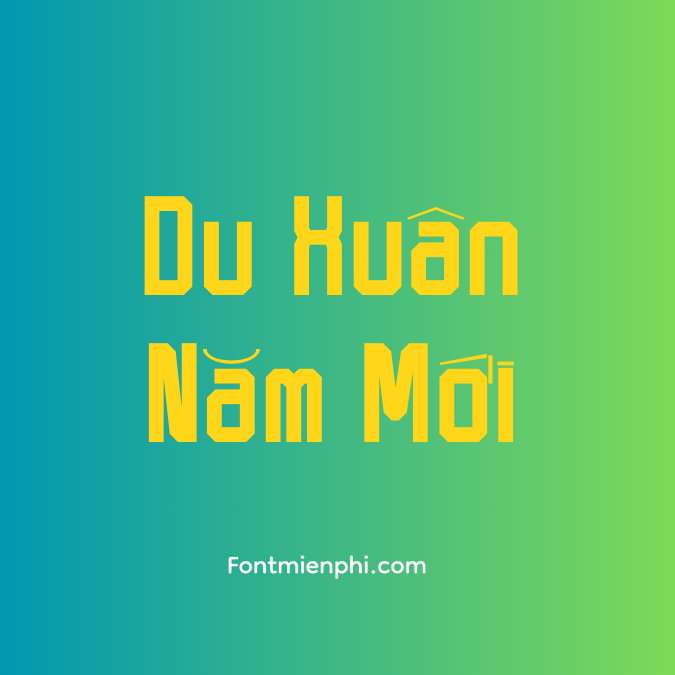
Font Việt hóa 1FTV VIP Vintage Camping
Font 1FTV VIP Vintage Camping là một kiểu chữ độc đáo, kết hợp giữa phong cách vintage cổ điển và sự hiện đại. Được thiết kế dành riêng cho các dự án liên quan đến du lịch, cắm trại và thiên nhiên, font này mang lại cảm giác gần gũi và thân thiện.
Đặc điểm nổi bật:
• Phong cách Vintage: Với các đường nét mềm mại và tinh tế, font này gợi nhớ đến những tấm bích họa cổ điển, thích hợp cho các sản phẩm mang tính kỷ niệm.
• Hỗ trợ tiếng Việt: Font được Việt hóa hoàn chỉnh, bao gồm đầy đủ các ký tự tiếng Việt như chữ có dấu, giúp người dùng dễ dàng sử dụng trong các dự án nội địa.
• Đa dạng ứng dụng: Có thể sử dụng trong thiết kế poster, bao bì sản phẩm, hay các ấn phẩm truyền thông liên quan đến hoạt động ngoài trời.
• Dễ đọc: Mặc dù mang phong cách cổ điển, font này vẫn đảm bảo tính dễ đọc, phù hợp cho cả tiêu đề và văn bản.
Việc sử dụng font 1FTV VIP Vintage Camping sẽ giúp tạo nên một bầu không khí ấm áp, gần gũi cho các sản phẩm hoặc sự kiện liên quan đến cắm trại và khám phá thiên nhiên. Font này không chỉ thu hút người nhìn mà còn thể hiện được phong cách sống tích cực và yêu thích phiêu lưu.